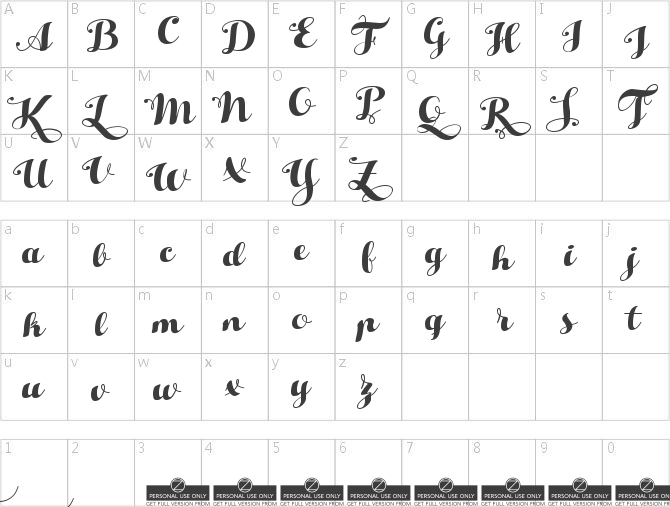
HelloScript TRIAL
HelloScript TRIAL介紹
HelloScript TRIAL字體字庫是一款讓人賞心悅目、百看不厭的英文字體,適合各類廣告和產品包裝設計應用,字體大小0.28MB,格式為ttf字體,上傳用戶是yinjun,作者/版權方為未知
HelloScript TRIAL效果圖